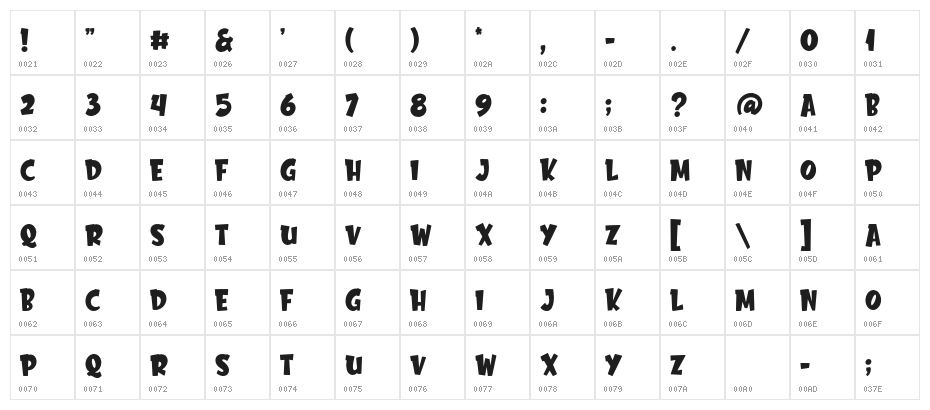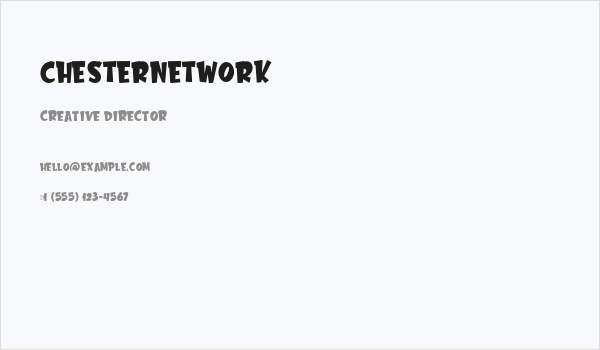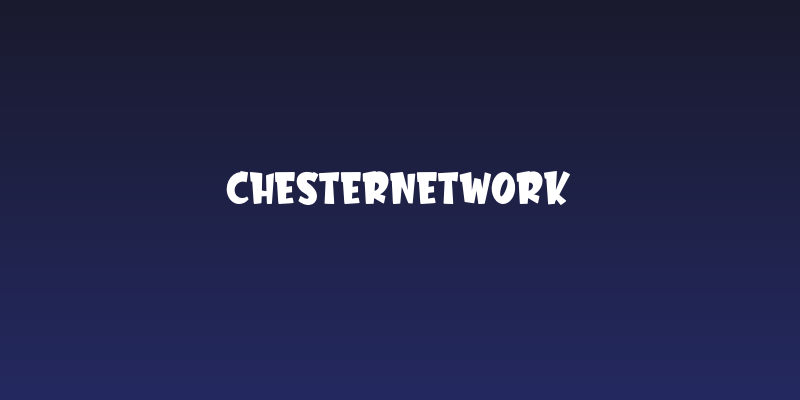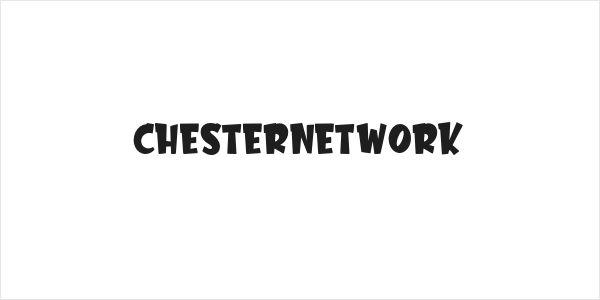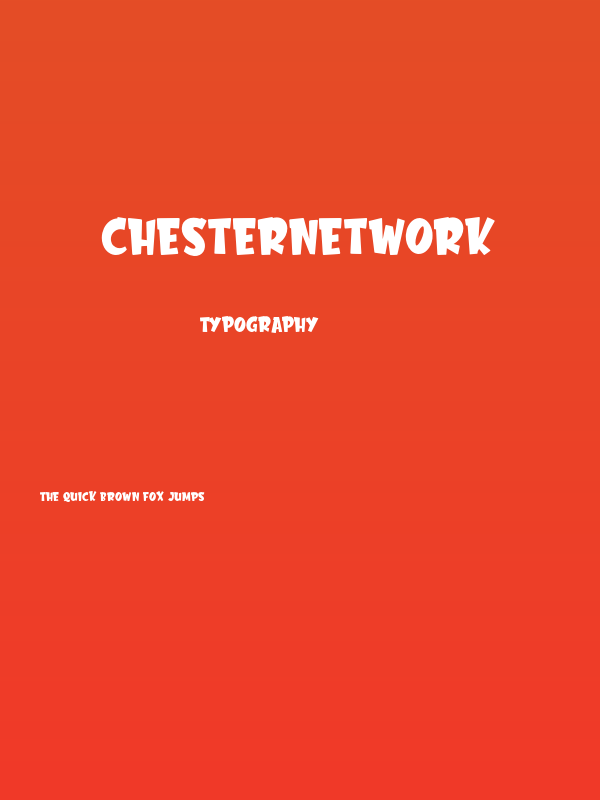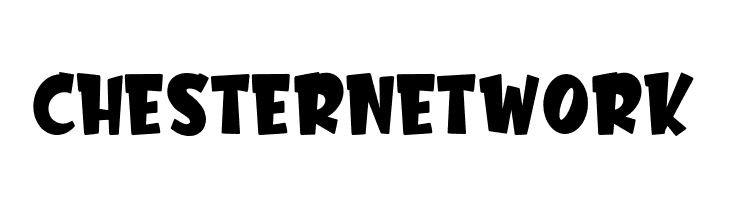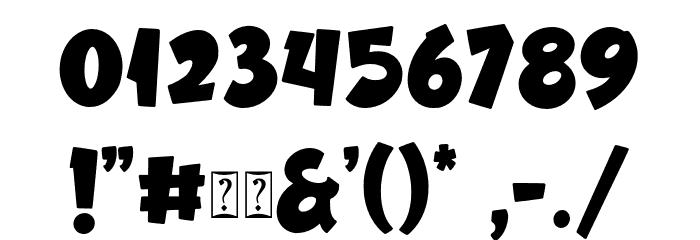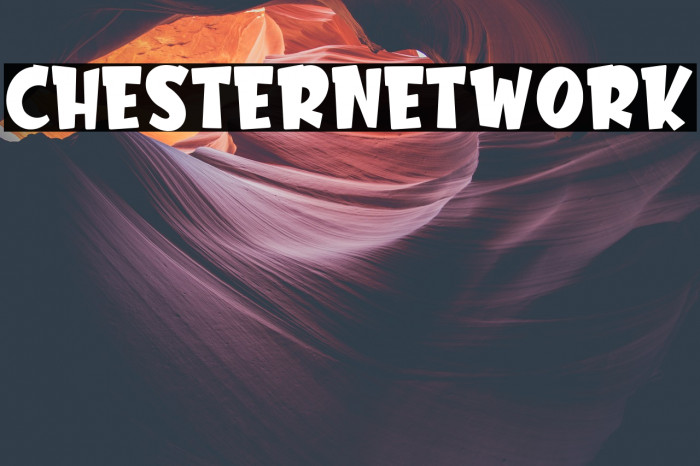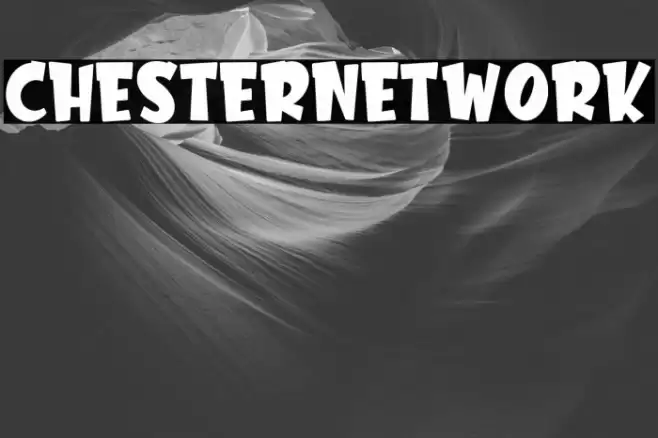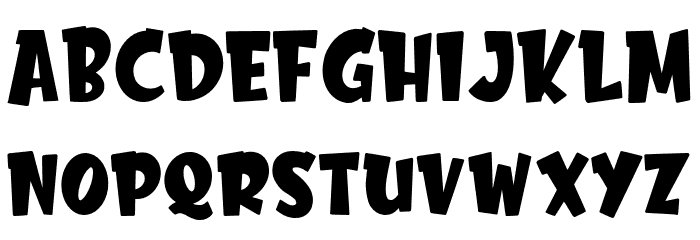
ChesterNetwork Font
✎ Cartoon
| Estilo geral | Playful, Quirky |
| Caso de uso | Headlines, Posters, Branding |
| Projetos propostos | Ideal for children's books, comic strips, playful branding, and eye-catching posters. |